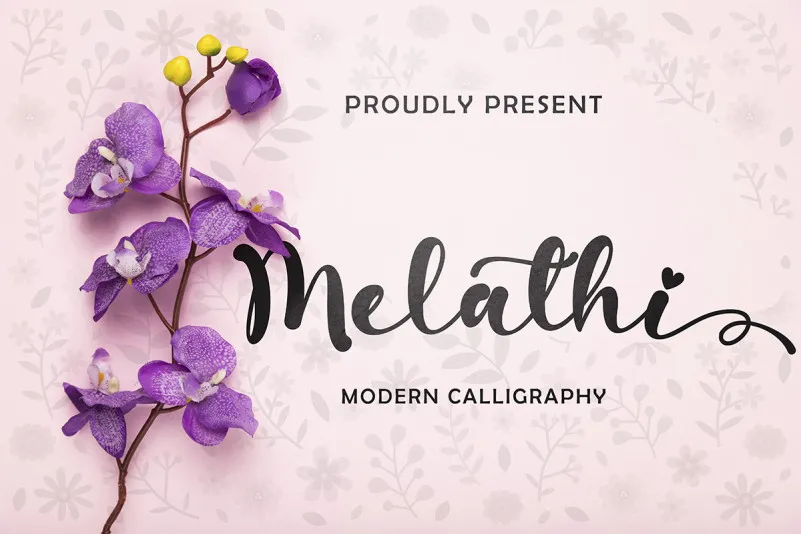
Melathi Script Font – Fonte Grátis
Melathi Script Font
Aqui está uma descrição embolada e envolvente para a página de download da fonte “Melathi Script Font”: Na categoria dos Fonts Script, encontramos “Melathi Script Font”, um tipo de letra romântica e doce que dança pelas linhas baselines. Este é o tipo de tipo que adicionará um brilho luxuoso a qualquer projeto gráfico que você estiver criando! Todas as suas letras têm uma elegância suave, como se cada caractere fosse capaz de contar uma pequena história com seus traços e formas delicadas. Seja para criar design gráfico para sua empresa ou para personalizar o seu site de maneira única, a “Melathi Script Font” está aqui para dar um toque especial. O grande ponto forte desta fonte é sua capacidade de acessar todas as suas incríveis gílias e ligaturas com facilidade. Com PUA (Propriedades Unicode Associadas) encodado, você terá acesso instantâneo a todos os detalhes que farão da “Melathi Script Font” uma escolha incomparável. Que tal adicionar um toque de luxo e romantismo ao seu design? A “Melathi Script Font” é perfeita para qualquer projeto que deseja se destacar!